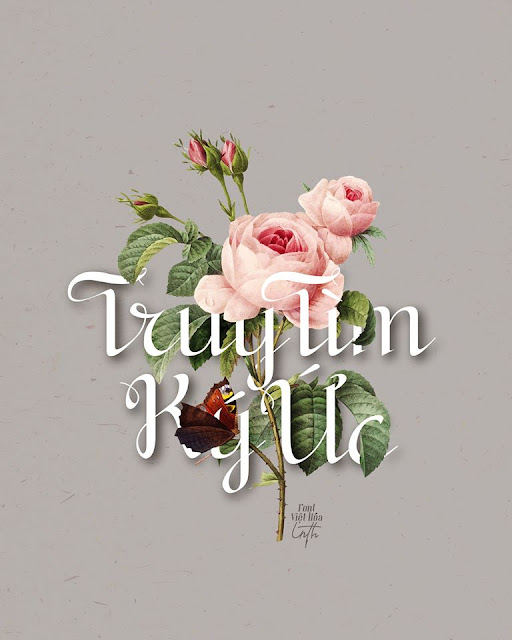
Giới thiệu về Font việt hóa LNTH Bryana Aningsih Shara
Trong thế giới thiết kế đồ họa, việc lựa chọn một Font Chữ phù hợp đóng vai trò quan trọng để truyền tải cảm xúc của tác phẩm. Font việt hóa LNTH Bryana Aningsih Shara là một ví dụ điển hình cho sự kết hợp giữa nét chữ viết tay phóng khoáng và sự tinh tế hiện đại. Đây là bộ phông thuộc phong cách Script, mang đến cảm giác gần gũi nhưng không kém phần sang trọng cho người xem.
Đặc điểm nổi bật của bộ font
Được thiết kế với các đường nét uốn lượn nhịp nhàng, bộ chữ này tạo nên một dòng chảy tự nhiên như nét bút thật. Điểm đặc biệt của phiên bản việt hóa bởi LNTH là các dấu tiếng Việt được tinh chỉnh kỹ lưỡng, đảm bảo sự cân đối và không bị lỗi hiển thị khi soạn thảo văn bản. Điều này giúp các bạn học sinh và giáo viên dễ dàng ứng dụng vào việc làm thiệp chúc mừng hoặc trình bày bài giảng điện tử sinh động hơn.
Ứng dụng thực tế của Font việt hóa LNTH Bryana Aningsih Shara
Nhờ vẻ ngoài thanh lịch, font chữ này thường xuyên được ưu tiên trong các dự án đòi hỏi tính thẩm mỹ cao như thiết kế logo thương hiệu, tiêu đề bìa sách hoặc thiệp cưới. Trong môi trường học đường, các em học sinh có thể dùng nó để trang trí báo tường hoặc làm portfolio cá nhân ấn tượng. Sự linh hoạt trong đường nét giúp phông chữ này nổi bật trên cả nền ảnh đơn giản lẫn phức tạp.
Lưu ý khi sử dụng trong thiết kế
Để phát huy tối đa vẻ đẹp của bộ font, bạn nên kết hợp nó với các phông chữ không chân (Sans Serif) tối giản. Sự tương phản giữa nét chữ bay bổng của LNTH Bryana Aningsih Shara và sự cứng cáp của font bổ trợ sẽ tạo nên một bố cục hài hòa và chuyên nghiệp. Đừng quên kiểm tra khoảng cách giữa các chữ cái để văn bản luôn dễ đọc.
Kết luận về bộ phông chữ đẹp